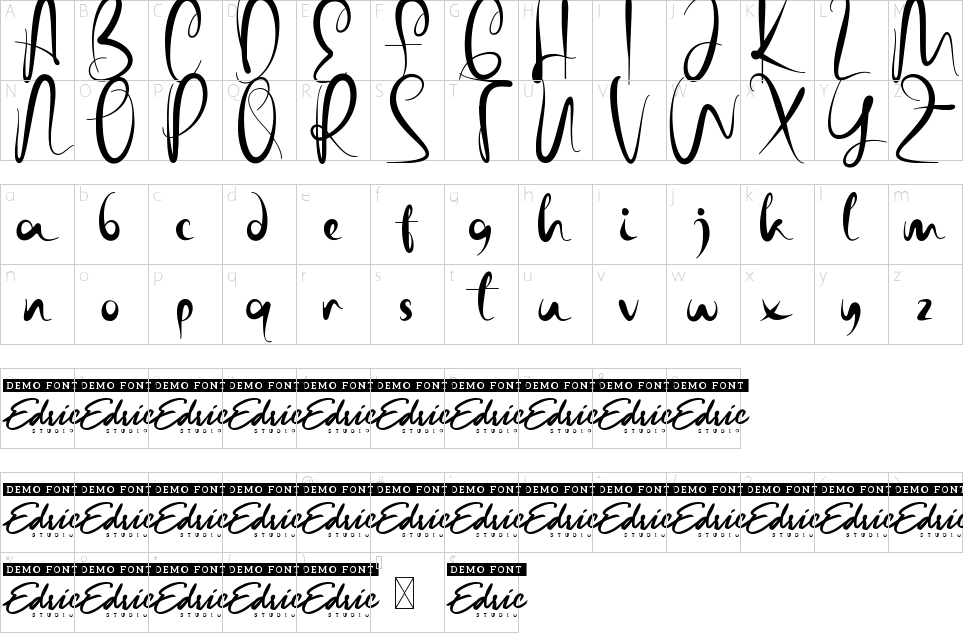
Descubra uma fonte única e elegante para seus projetos gráficos com a Madira Queen font. Desenvolvida pelo designer EdricStudio, essa fonte traz uma sensação de sofisticação e elegância, ideal para design de nomes e logotipos. A Madira Queen font está disponível para download tanto em Windows quanto em Mac, e já foi baixada por muitos designers apaixonados. Composta em 289 caracteres, esta fonte é uma ótima escolha para quem busca um equilíbrio perfeito entre elegância e modernidade. Adquira sua versão hoje e transforme a aparência de seus projetos.